1. 부크크체
종이책 인쇄에 적합한 책을 쓰는 작가와 읽는 독자를 모두 만족시키는 폰트입니다. 붓으로 쓴 듯한 획을 살려 전통적인 명조체의 느낌을 주는 폰트입니다.
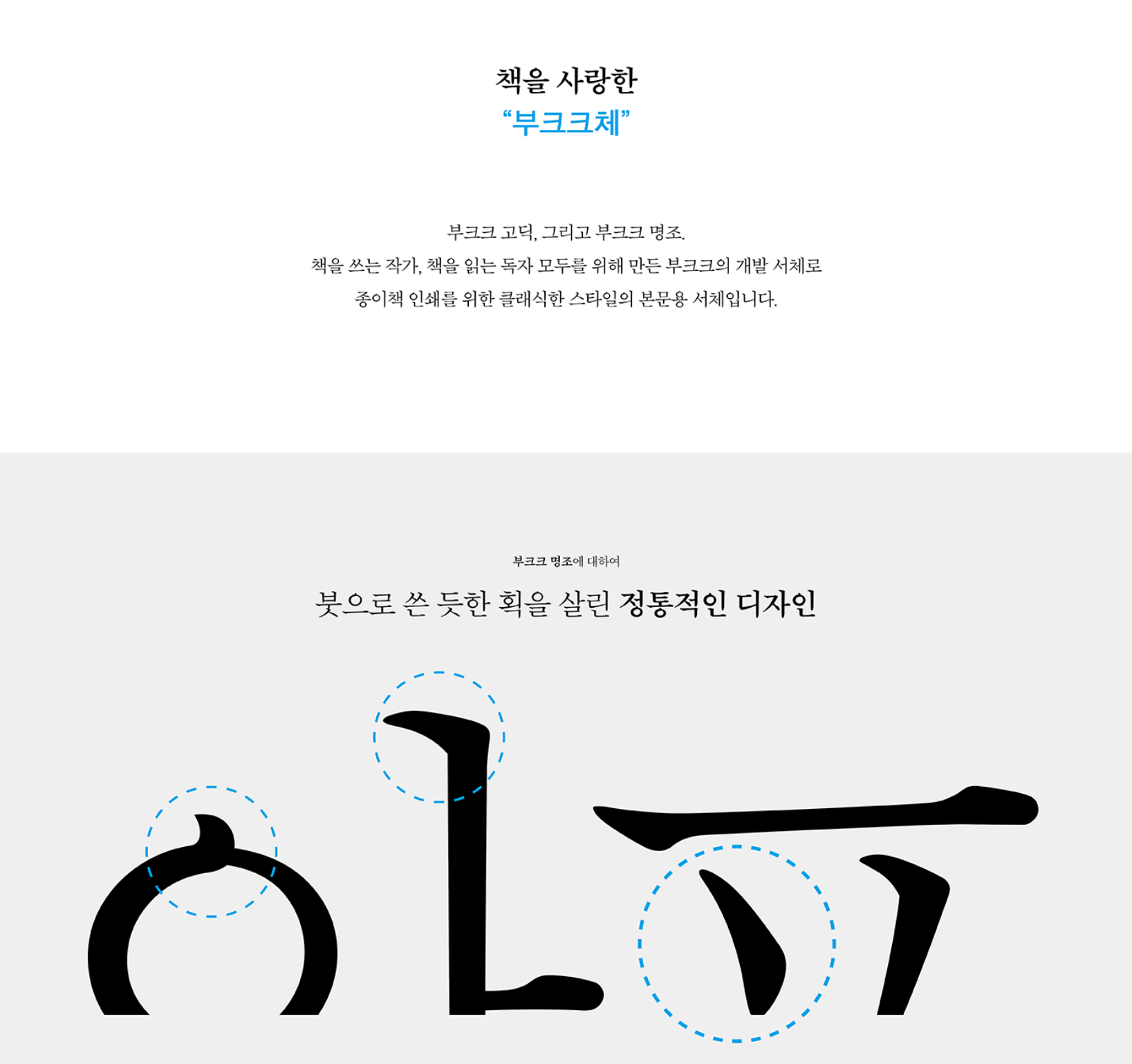
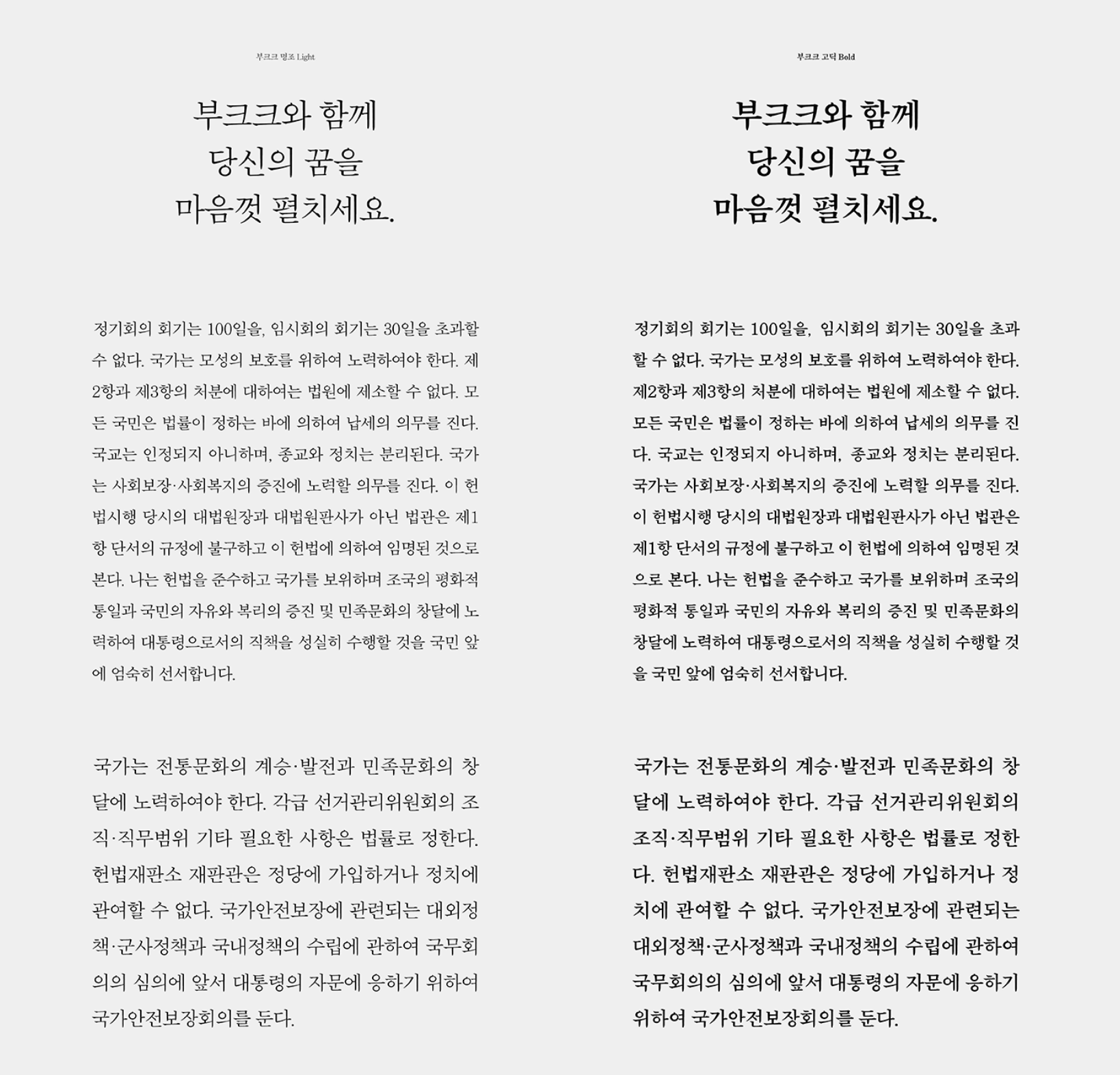
2. 조선일보 명조체
조선일보에서 제공하는 무료폰트로 명조체 뿐만 아니라 조선100년체, 고딕체, 궁서체 등 다양한 폰트를 무료로 배포하고 있습니다. 조선일보명조체는 기존 명조체의 획을 단순화해 현대적 미감을 갖춘 폰트입니다. 조선일보는 2007년에 배포를 시작한 조선일보명조체를 시작으로 창간 100주년을 맞아 조선일보 전용서체 9종을 무료로 배포하고 있습니다.
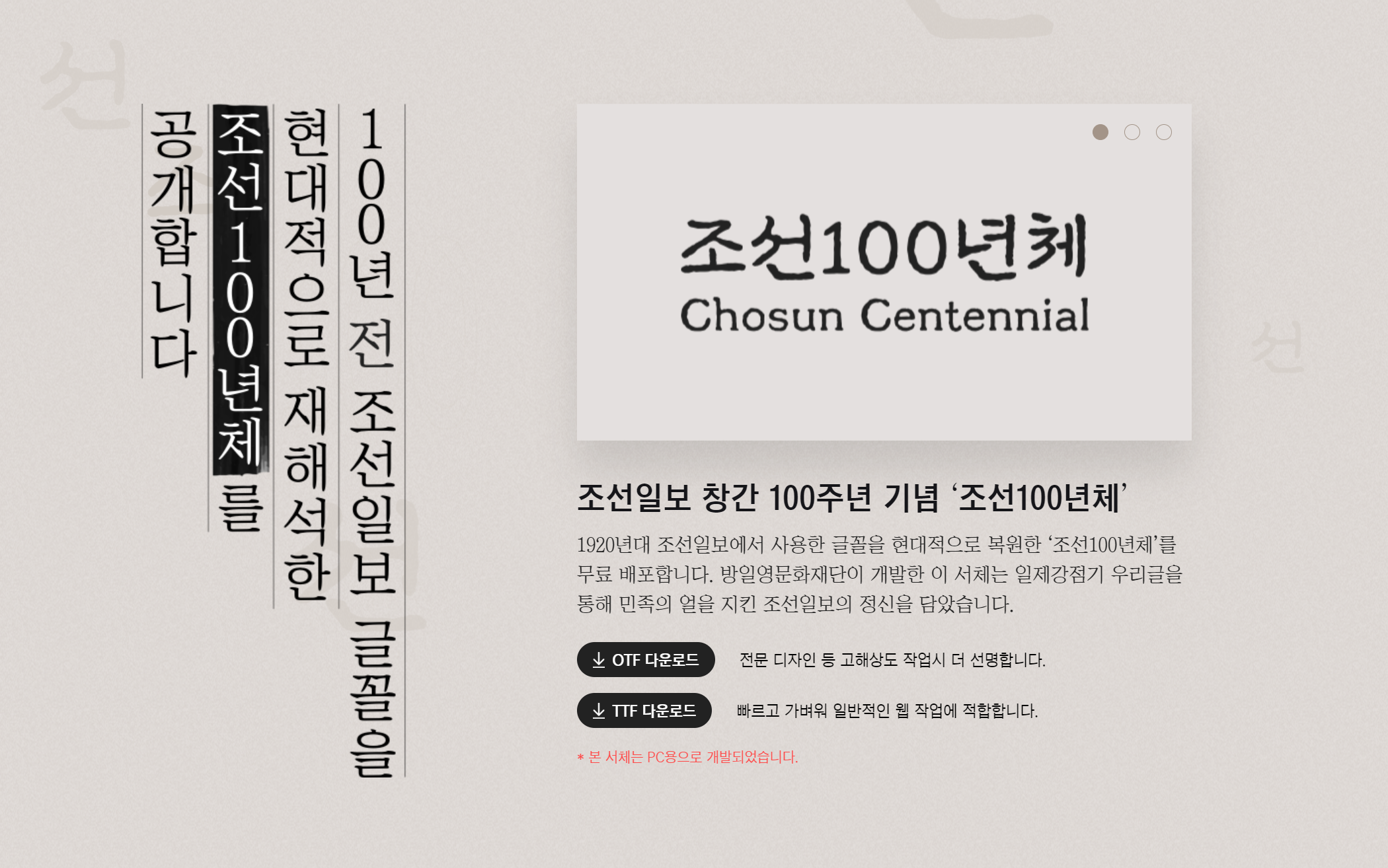
3. 경기천년바탕체
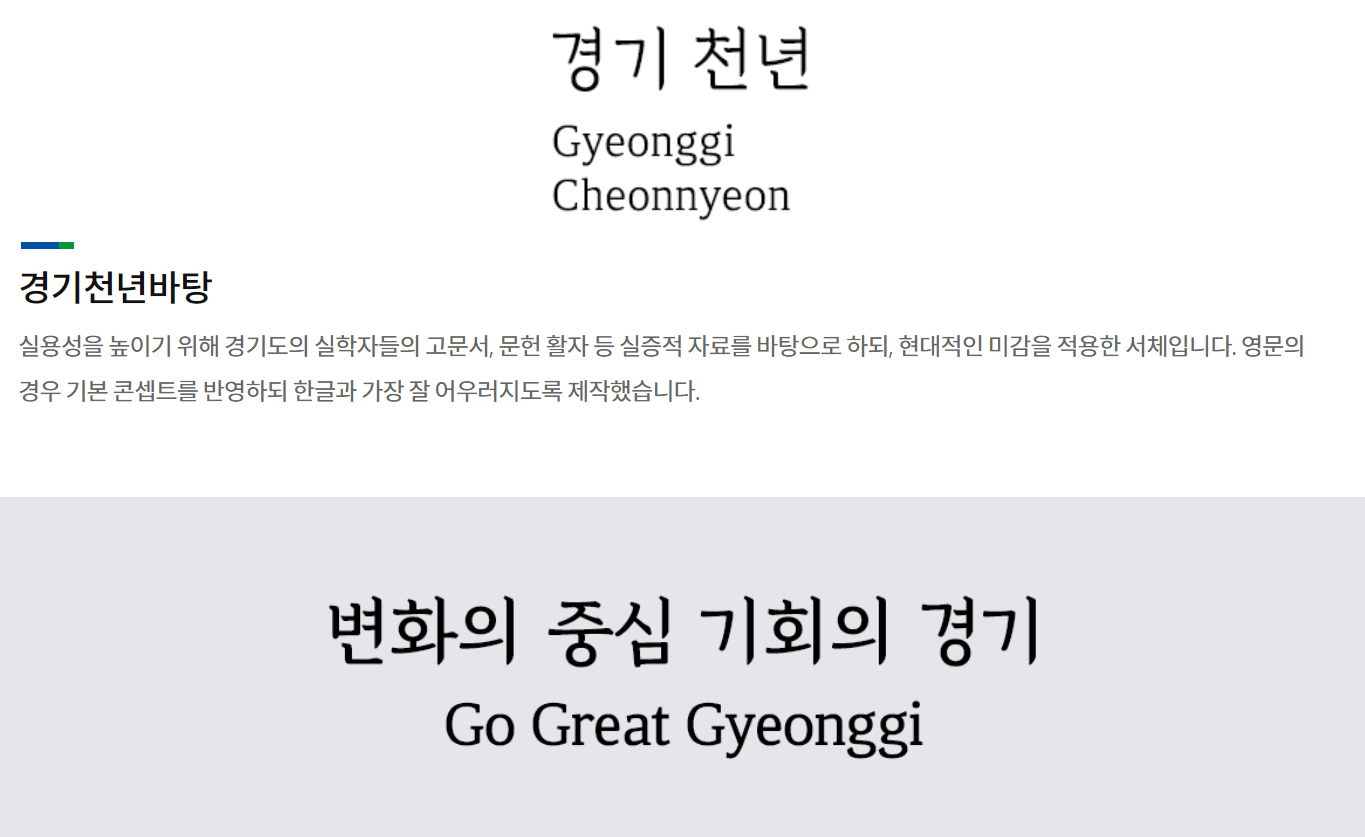
4. 을유1945
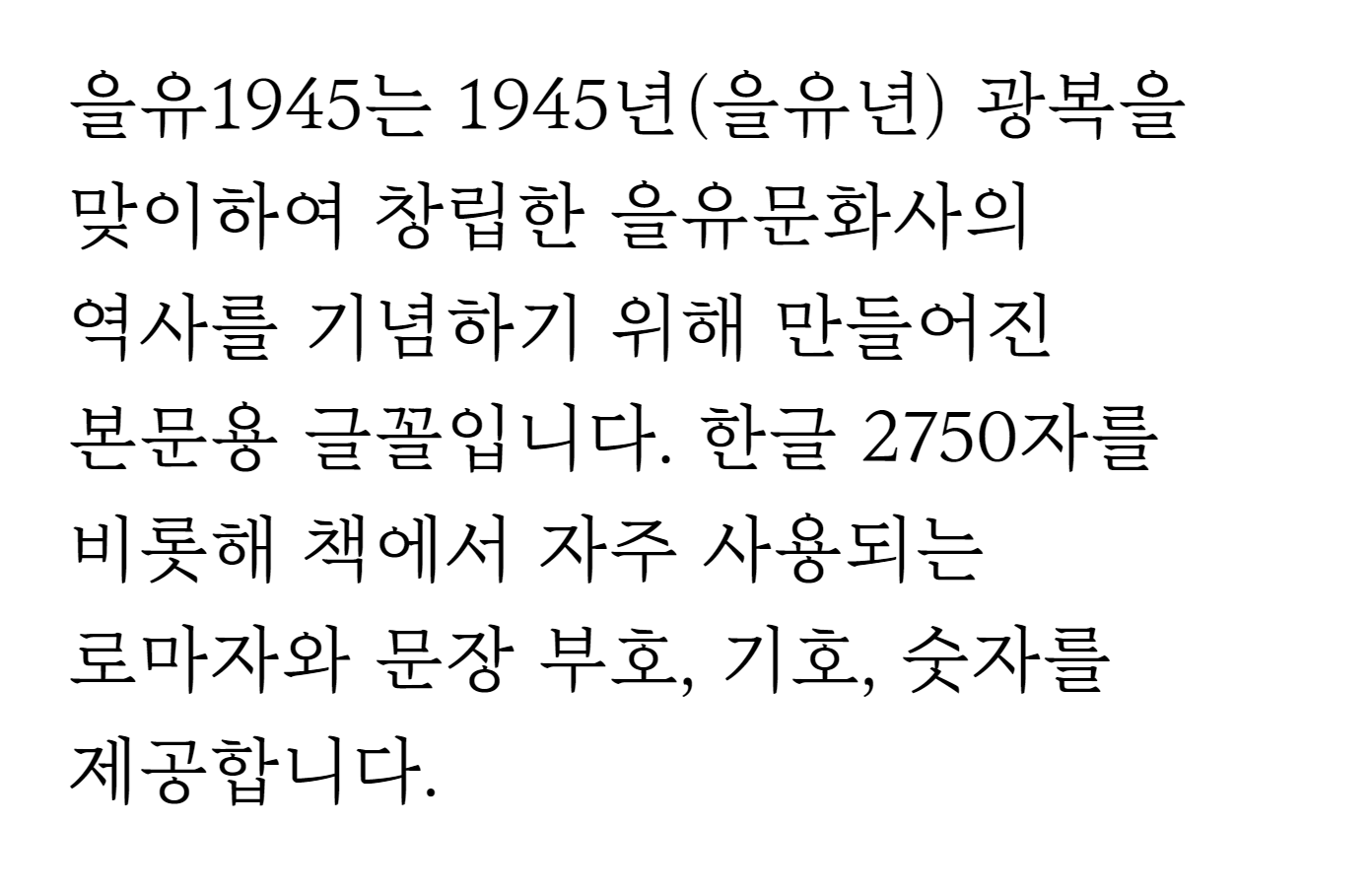
5. KopubWorld 바탕체
KoPub 서체에서 구현되지 않았던 옛 한글과 한자, 일본어, 라틴어, 러시아, 히브리어, 아라비아어, 산스크리트어 등 다양한 언어를 포함하여 업그레이드되었습니다. KopubWorld 고딕체와 함께 인기가 많은 폰트입니다.